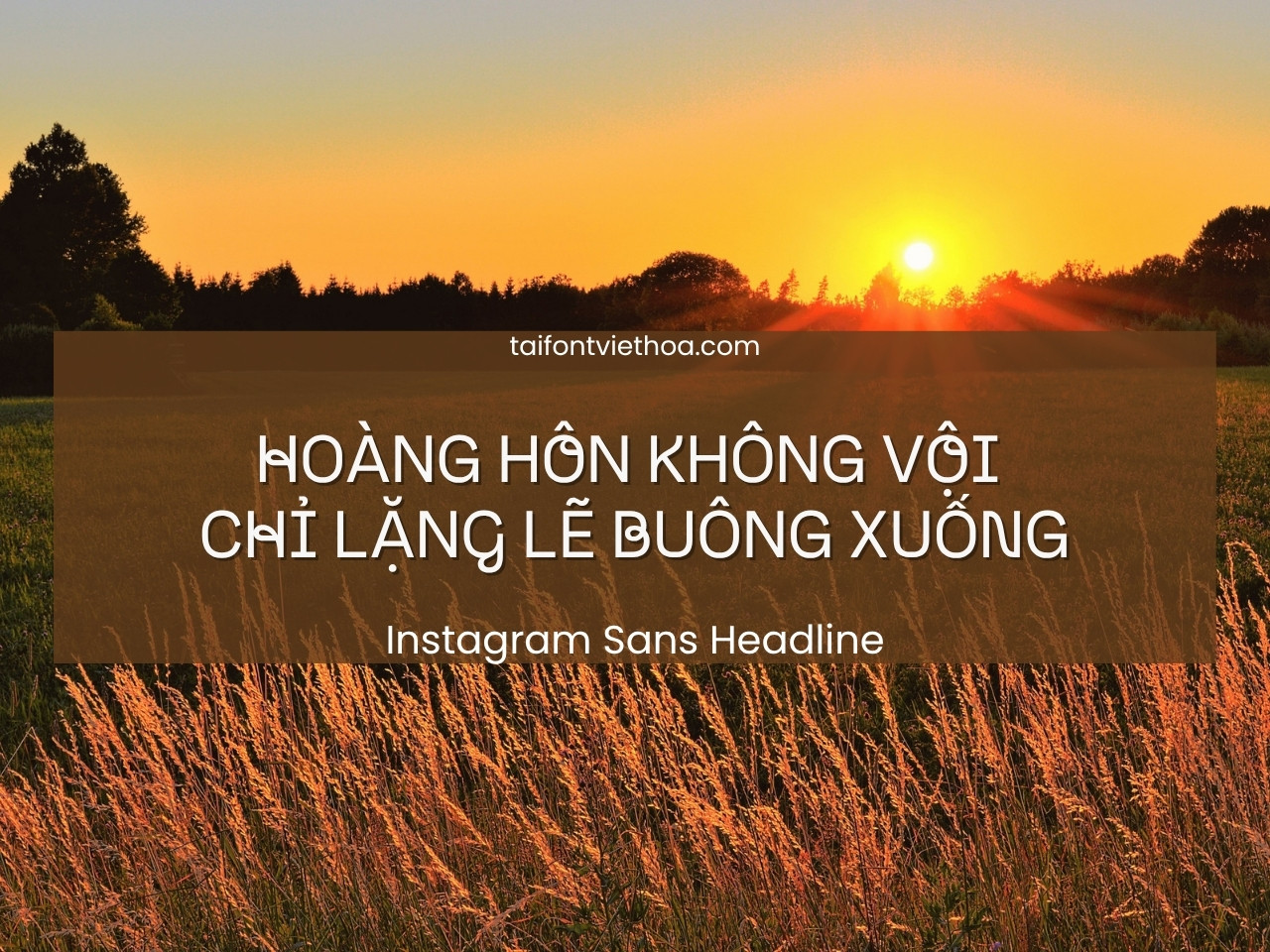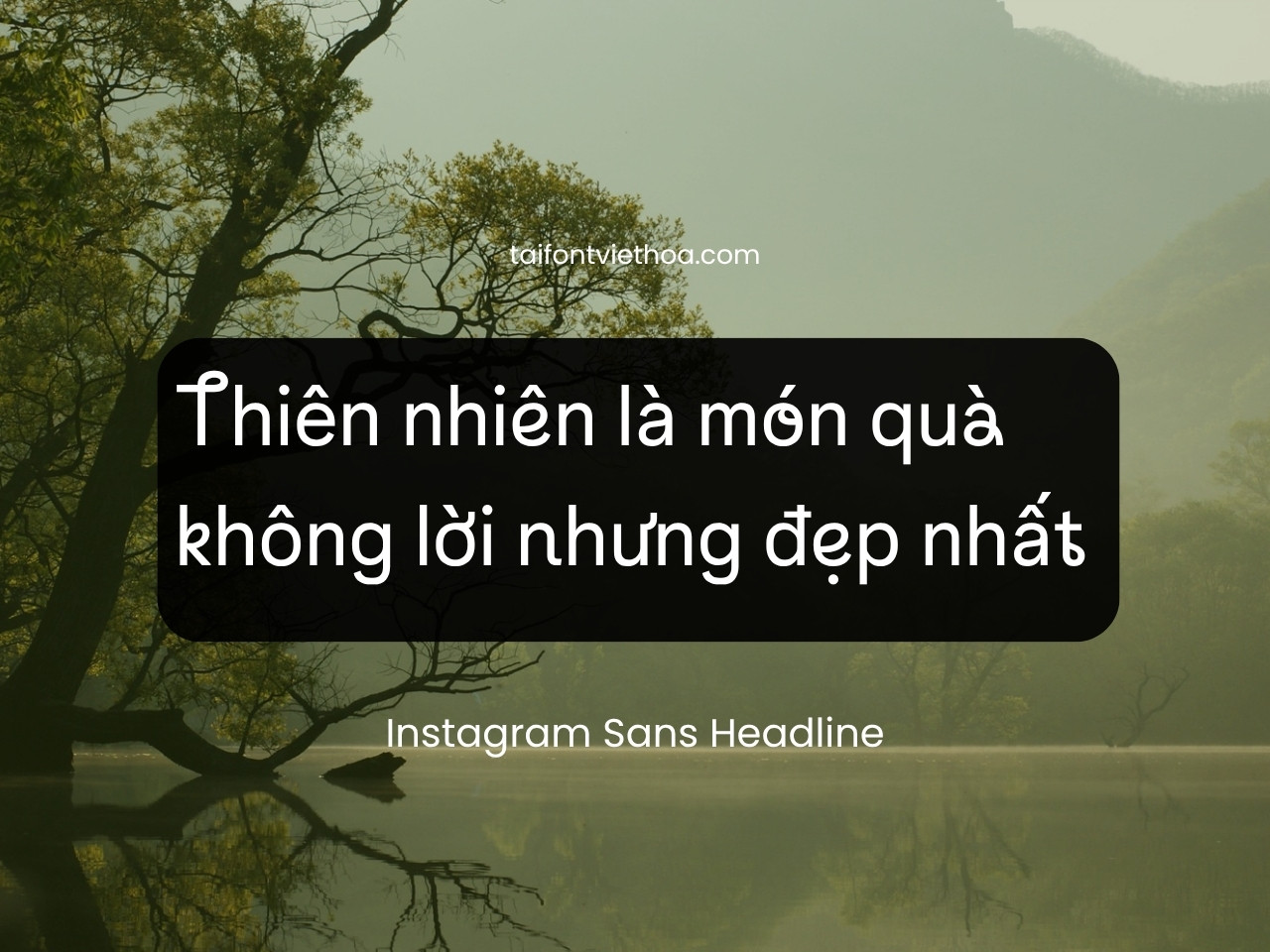
Font việt hóa Instagram Sans Ui đầy đủ (Headline)
Giới thiệu về font Instagram Sans UI
Instagram Sans là bộ font độc quyền được Meta (công ty mẹ của Instagram) giới thiệu vào giữa năm 2022, nhằm củng cố bản sắc thương hiệu và nâng tầm trải nghiệm giao diện người dùng trên nền tảng. Trong đó, biến thể Instagram Sans UI là kiểu chữ dùng cho tiêu đề, giao diện hệ thống và các điểm nhấn hiển thị trong ứng dụng. Bộ font được thiết kế bởi đội ngũ nội bộ của Instagram kết hợp cùng các chuyên gia typographer quốc tế, với phong cách sans-serif hiện đại, trung tính và có tính toàn cầu cao. Font hỗ trợ hơn 140 ngôn ngữ sử dụng hệ chữ Latinh, Cyrillic, và Thái.
Phiên bản Việt hóa được thực hiện bởi Christy Silva, giữ nguyên tinh thần thiết kế của bản gốc và đảm bảo hiển thị chuẩn tiếng Việt. Tất cả các ký tự có dấu đã được căn chỉnh lại chi tiết theo hệ thống tỷ lệ gốc của Instagram Sans UI. Font này đã được taifontviethoa.com chọn lọc, thử nghiệm thực tế và chia sẻ lại cho cộng đồng thiết kế tại Việt Nam – đặc biệt những ai cần một font giao diện hiện đại, hợp xu hướng và có khả năng ứng dụng mạnh trong thiết kế digital.
Đặc điểm thiết kế và khả năng ứng dụng
Instagram Sans UI sở hữu hình khối gọn gàng, các chữ cái được thiết kế với độ cong vừa phải ở phần góc tạo nên sự mềm mại và gần gũi. Phần thân chữ cao (high x-height) tăng cường khả năng đọc trên thiết bị di động. Các biến thể Headline mang độ đậm rõ nét, lý tưởng cho phần tiêu đề, chữ call-to-action, hoặc các đoạn text quan trọng cần nhấn mạnh.
Font này đặc biệt phù hợp với các thiết kế ứng dụng di động, giao diện web, truyền thông mạng xã hội, banner quảng cáo, hoặc hệ thống hiển thị dành cho người dùng trẻ. Các ngành nghề lý tưởng gồm: công nghệ, spa, mỹ phẩm, ẩm thực, sự kiện, ảnh cưới, đặc biệt là các thương hiệu hướng đến phong cách trẻ trung và hiện đại.